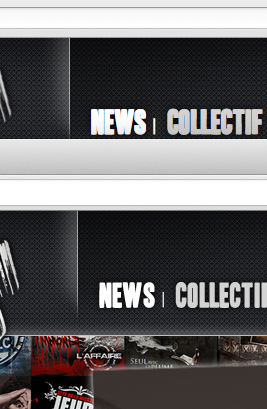
Voilà donc ma problématique du jour; j'ai codé un site, y ai inclut des polices via @font-face, et ces polices apparaissent plus épaisses et presque illisibles sur Firefox. Comme sur le ScreenCapture ci dessous. (Firefox en haut et Chrome en bas).
Bonjour. Ce problème est connu: la graisse des polices est plus importante sur Firefox et Opéra que sur webkit. Il faut aussi prévoir l'espacement entre les caractères, variable surtout d'un OS à l'autre.
A cause de cela, certains designs trop spécifiques peuvent se voir complètement cassés par certains browers.